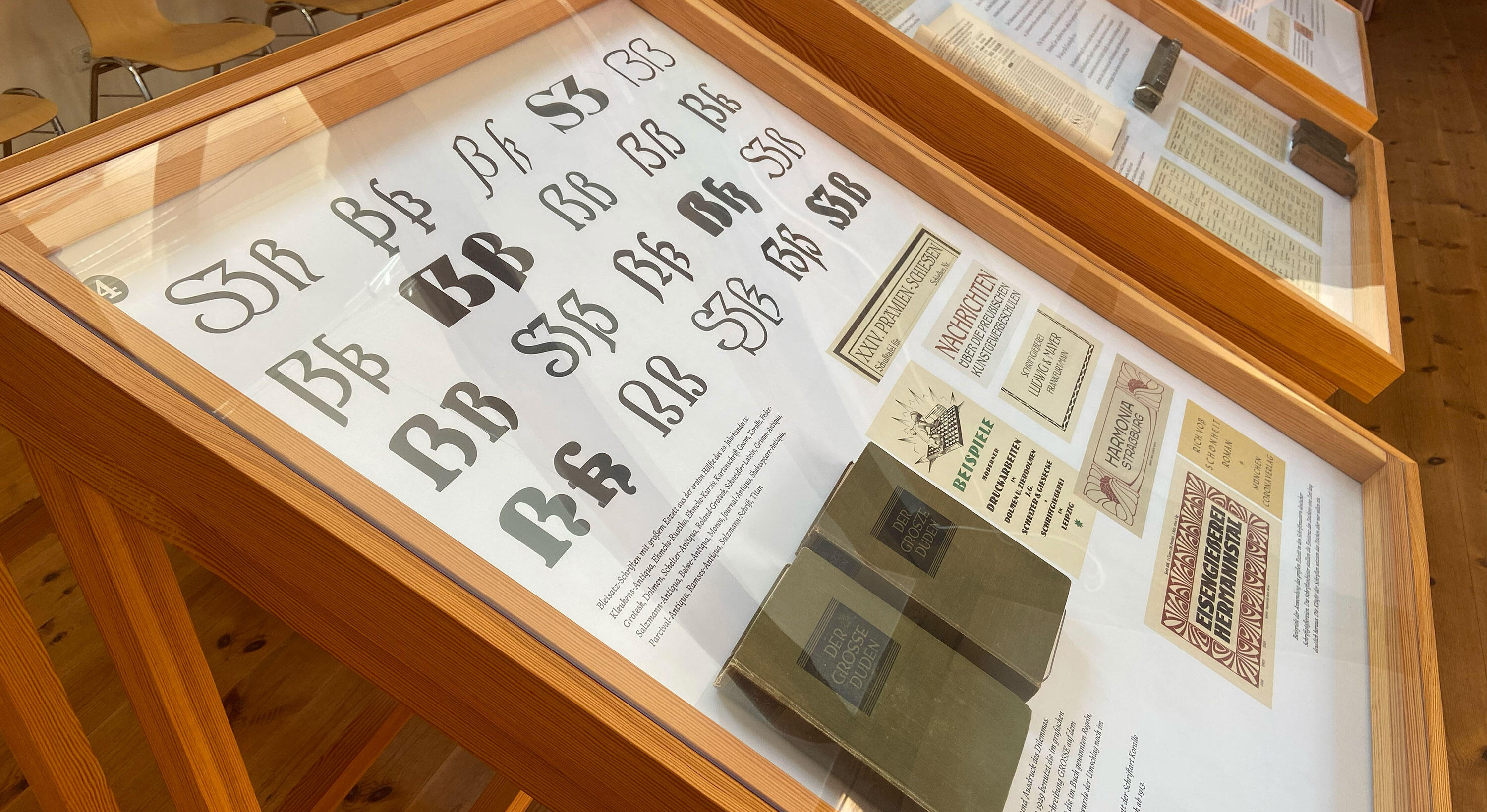
Das Eszett: So streitbar wie liebenswert. Ein Buchstabe, der aus der Reihe tanzt. Das Eszett ist der einzige Buchstabe, der ausschließlich im deutschen Alphabet existiert, und findet sich dort bereits in deutschen Handschriften vor der Erfindung des Buchdrucks vor über 500 Jahren. Dies macht das Eszett zu einem Stück deutscher Kulturgeschichte.
Über Herkunft, Anwendung, Form und Nutzen wird jedoch bereits seit mindestens dem 19. Jahrhundert heftig gestritten. Gerade wegen der vielen Unklarheiten über das Wesen des Buchstabens entwickelte sich im Laufe der Zeit ein spannender und einzigartiger Formenreichtum.
Das Eszett ist zudem ein besonderer Buchstabe, weil es über Jahrhunderte ausschließlich als Kleinbuchstabe existierte. Die Einführung des großen Eszett wurde seit dem 19. Jahrhundert immer wieder vorgeschlagen und debattiert, gelang jedoch erst im dritten Anlauf im 21. Jahrhundert.
Eine neue Sonderausstellung der Pavillon-Presse Weimar erzählt diese Geschichte.